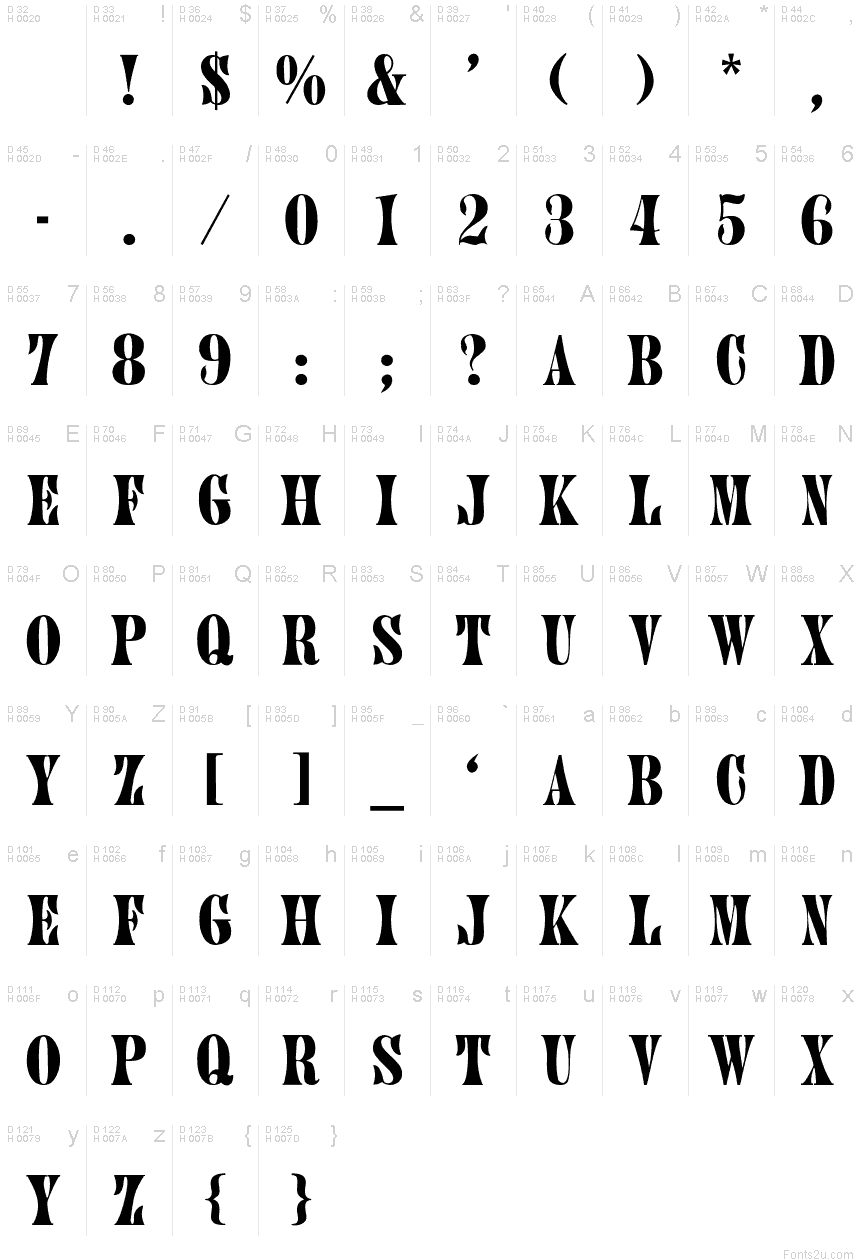
Jennifer Thin to darmowy, retro krój pisma typu display z dramatycznymi, przypominającymi wstążki pociągnięciami, które wycinają białe kanały w pełnych, czarnych literach. Litery wydają się niemal wyrzeźbione, z zamaszystymi krzywiznami i wąskimi pasmami negatywowej przestrzeni, tworząc hipnotyczny, psychodeliczny rytm. Krój posiada wyrazisty, plakatowy charakter, który natychmiast przyciąga uwagę, zwłaszcza w dużych rozmiarach, gdzie skomplikowane wewnętrzne kształty mogą naprawdę odetchnąć.
Dzięki Jennifer Thin uzyskasz wyrazisty element, który błyszczy na okładkach płyt, plakatach festiwalowych, w brandingu modowym, zinach, tytułach książek i odważnych projektach opakowań. Ten darmowy font świetnie sprawdza się w zestawieniu z prostym krojem bezszeryfowym, dzięki czemu jego ozdobne krzywizny pozostają w centrum uwagi. Ustaw go w dużym rozmiarze, daj mu przestrzeń i pozwól, by jego atramentowe, falujące kształty przemówiły same za siebie.